Французские акценты в рукописном шрифте: как проверить набор
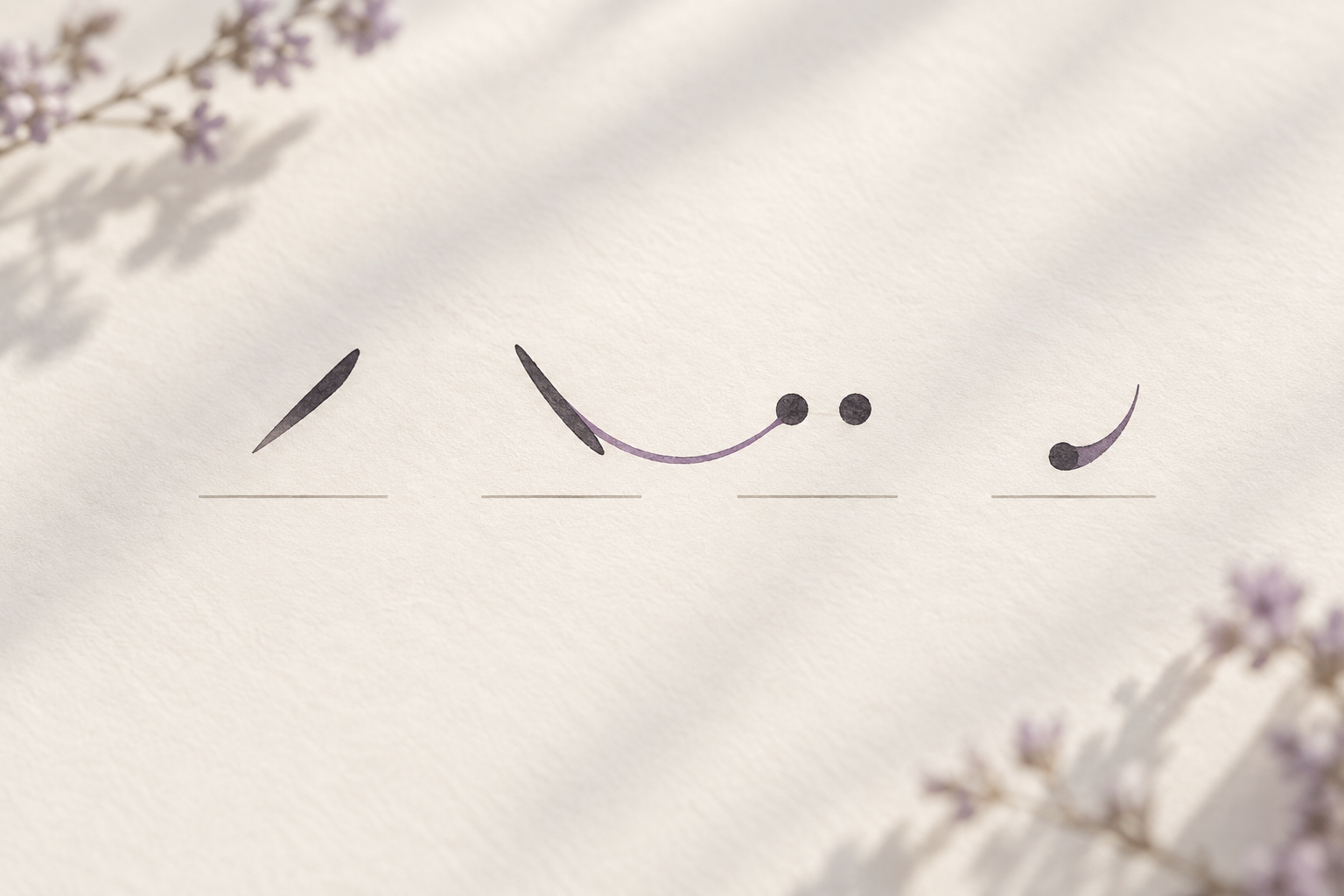
Французский текст проверяет рукописный шрифт не только обычными латинскими буквами: в нём встречаются острые и грависные ударения, циркумфлекс, трема, седиль и лигатура œ. Чтобы надпись не распадалась на привычные буквы и случайные подстановки, сначала составьте набор нужных знаков, затем проверьте форму, кодирование и слова целиком. Ниже — практический маршрут от списка символов до короткой корректуры.
Какие французские знаки включить в проверку
Не начинайте с попытки «добавить все акценты». Сначала определите, где будет использоваться шрифт: в коротких именах, меню, открытках, длинном тексте или учебных материалах. От этого зависит, достаточно ли базовых французских слов или понадобится более широкий набор латинского расширения. Для первого теста подготовьте строчные и прописные формы основных букв с диакритикой:
- острое ударение: é и É;
- гравис: à, è, ù и прописные À, È, Ù;
- циркумфлекс: â, ê, î, ô, û и Â, Ê, Î, Ô, Û;
- трема: ë, ï, ü, ÿ и Ë, Ï, Ü, Ÿ;
- седиль: ç и Ç.
Для французского текста важны и знаки, которые не являются просто буквой с акцентом. Проверьте œ и Œ в словах cœur, sœur, œuvre; æ и Æ тоже встречаются, например в выражении ex æquo. Их частотность и необходимость зависят от аудитории и материала, поэтому принимайте решение по реальным словам, а не по длинному списку из случайных глифов.
Как собрать короткий, но содержательный тест
Одна строка со всеми акцентированными буквами быстро выявляет пропуск, но плохо показывает ритм. Составьте небольшой контрольный текст из разных типов слов. Например: «Élève, déjà, Noël, où, château, façade, naïve, cœur et œuvre». В этой строке соседствуют разные отметки, знаки в начале и середине слова, сочетания с обычными буквами и лигатуры.
Затем добавьте формы, которые проверяют прописные знаки: «À Noël, Ève goûte une crème; ÇA va?». Это не литературный текст, а тестовая строка: её задача — показать, не уезжают ли акценты над заглавными, не сталкиваются ли они с верхним краем строки и не становятся ли слишком мелкими при уменьшении. Для естественности дополните тест именами, названиями и фразами, которые действительно планируете набирать.
Полезно сделать три образца разной длины:
- Панель знаков — пары строчных и прописных форм, удобно расположенные рядом: é É, è È, ç Ç, œ Œ.
- Набор слов — слова с каждым типом отметки и лигатурой, чтобы оценить сочетание символов.
- Короткий абзац — реальное предложение с обычными буквами, знаками препинания и несколькими акцентами.
Панель помогает найти пропущенный символ, слова показывают рисунок в привычном окружении, а абзац выявляет проблемы с общей плотностью и строкой. Для кириллическо-латинского набора полезно добавить один и тот же русский и французский фрагмент: так легче заметить, не выглядят ли французские буквы чужими по толщине, наклону или высоте.
Нарисуйте диакритики как часть буквы
Акцент не должен выглядеть случайным украшением, прилепленным после завершения алфавита. Сначала сравните его характер с основными штрихами шрифта: одинаково ли мягкие окончания, подходит ли толщина, совпадает ли общий наклон. В рукописном стиле знак может быть живым, но его движение должно казаться продолжением той же руки.
Работайте с формами группами. Сравните острое и грависное ударения: отличаются ли направление и вес, не спутал ли рисунок их силуэты? Проверьте циркумфлекс: две стороны должны образовывать понятную вершину и не превращаться в почти прямую черту. Трема состоит из двух отдельных точек; если они слишком маленькие или далеко разнесены, знак теряет связь с буквой. Седиль должна быть различима у основания «c», не мешая соседнему символу.
Сделайте несколько проверок высоты. Надстрочный знак может выглядеть аккуратно на крупном образце, но столкнуться с верхней границей строки после экспорта или при уменьшении. Посмотрите на одинаковые акценты над буквами с разной формой: над узкой «i» и широкой «e», над прописными и строчными. Если шрифт рукописный, допускайте небольшие оптические различия, но сохраняйте узнаваемую систему.
Для œ не копируйте автоматически отдельные «o» и «e», поставленные рядом. Сравните лигатуру с темпом письма и интервалами соседних пар: она может быть компактнее, но не должна превращаться в неразборчивое пятно. Проверьте её в словах cœur и œuvre, а не только отдельно. В рукописном шрифте непрерывное движение пера особенно заметно: если соединение ломает привычный ритм, упростите форму, сохранив различимость.
Проверьте кодирование, а не только картинку
Когда символ на экране похож на нужный, это ещё не доказывает, что в файле шрифта есть правильный глиф. Строка может показывать подстановку из другого шрифта, а буква с акцентом в Unicode иногда представима как готовый символ или как базовая буква вместе с комбинируемым знаком. Эти последовательности могут выглядеть одинаково, хотя проверка набора и поведение приложений различаются.
Французский набор становится надёжным, когда диакритики и лигатуры проверены одновременно как рисунки, как кодируемые символы и как часть реального текста. Подготовьте слова своей аудитории, сопоставьте французскую латиницу с кириллицей, откройте экспортированный файл в целевых приложениях и исправляйте конкретные сбои. Так акценты останутся частью почерка, а не случайными исключениями.